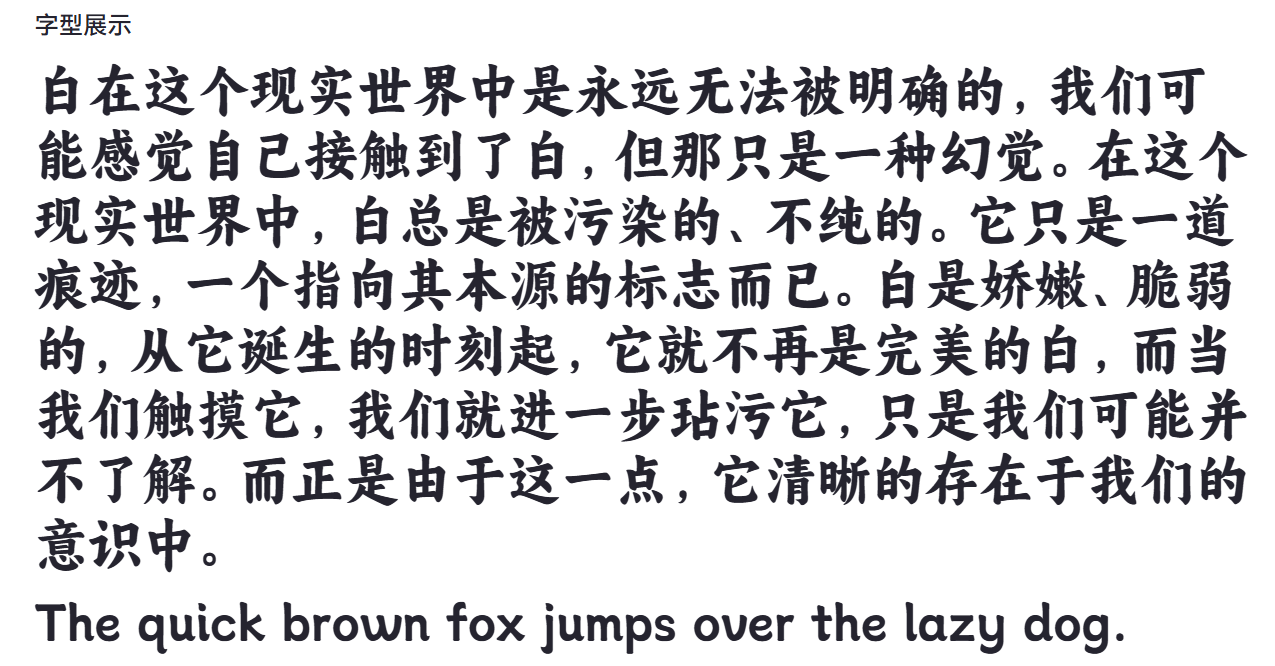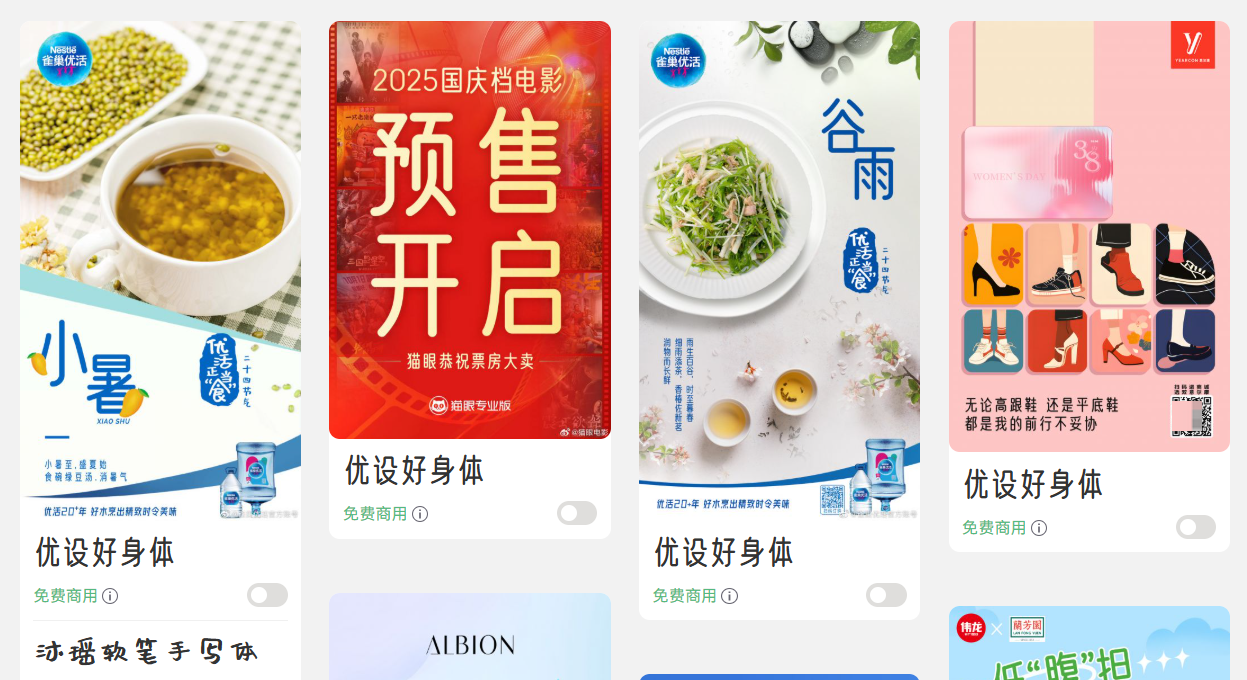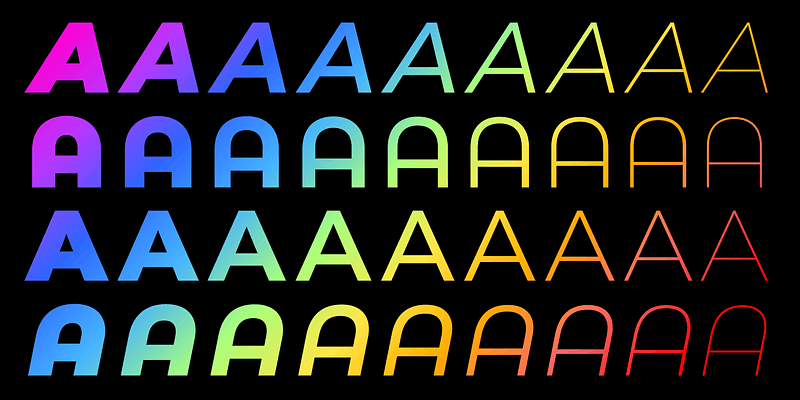
适合电影行业的字体推荐!8款适用于影视设计的字体
从电影海报、片名设计,再到预告片字幕、宣传物料,合适的字体往往能够帮助画面更好地去表达影片主题。在电影中,一款字体不仅承担着信息传递的作用,也会影响观众对影片风格的第一印象。而不同类型的电影对于字体的需求也有所区别,例如悬疑电影通常需要具有沉稳感的字体,科幻电影偏向简洁现代的设计,而文艺电影则更注重字体与画面氛围之间的协调。今天本文整理出了 8 款适合电影行业使用的字体素材,一起来看看有没有适合你的吧!
1、阿里妈妈东方大楷
阿里妈妈东方大楷是一款具有传统书法气息的中文字体,它整体笔画舒展,字体结构中保留了东方书写特点,适合用于具有文化背景或历史氛围的电影设计。如果是古装电影、武侠电影或历史题材电影,阿里妈妈东方大楷也能够帮助画面增加传统文化感。
我们还可以将它与水墨背景、古建筑元素、人物剧照等视觉内容来进行搭配,进一步提升电影中的传统文化氛围。
2、优设好身体
电影海报中的片名往往需要快速吸引观众注意力,因此标题字体需要具备一定辨识度。优设好身体的字形具有极强的视觉表现力,文字排列后能够形成较好的视觉焦点,轻松抓住观众的目光,可以用于动作电影、商业电影、活动宣传海报等设计。
对于要制作电影预告图、宣传海报或者社交媒体推广图片的设计师来说,可以考虑将优设好身体作为标题字体使用。
3、Montserrat
Montserrat 是一款海外常用的无衬线字体,整体风格简洁现代。它最大的特点是结构清楚,阅读体验较好。在电影行业字体的使用场景中,Montserrat 比较适合搭配极简风格、都市题材或者科幻类型电影海报。它不会抢占画面主体,同时能够呈现较强的现代感。在宣传电影时,如果需要同时展示英文片名、导演信息或者制作团队信息,Montserrat 也可以帮助你保持较好的视觉统一。
4、Bebas Neue
在电影海报、影视预告片标题以及商业宣传设计中,Bebas Neue 是比较常用的字体了。因为它的字体比例较为修长,排列后具有明显的视觉方向感,做为标题字体再合适不过。而在一些动作电影、冒险电影或者体育纪录片等类型设计中,Bebas Neue 也能够帮助你来强化画面的力量感。
不过,由于字体风格比较突出,使用时需要注意与背景图片的搭配。如果文字内容较多,则需要合理控制字号和间距,避免影响整体阅读效果。
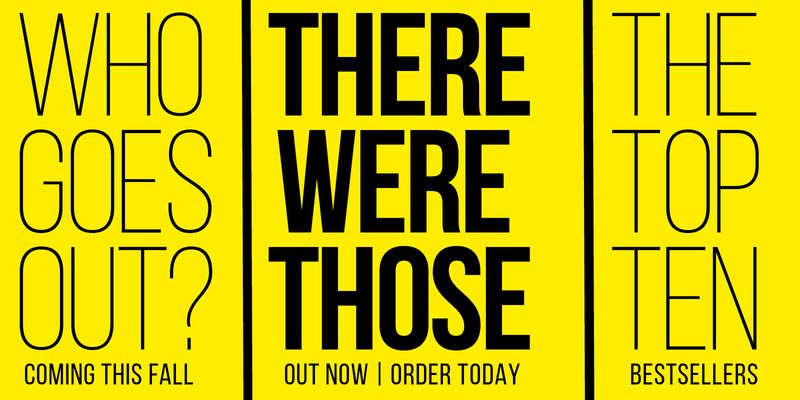
5、Playfair Display
对于艺术电影、历史题材电影或者爱情电影海报来说,字体本身的细节能够增加画面的精致感。而 Playfair Display 这样一款带有衬线特点的字体,可以帮助你保持电影中优雅和稳定的风格。对于一些强调质感和文化氛围的电影设计项目来说,Playfair Display 就比较适合作为片名、章节标题或者宣传语使用。在使用时,我们可以将它与摄影作品、黑白影像、复古色调等视觉元素搭配。
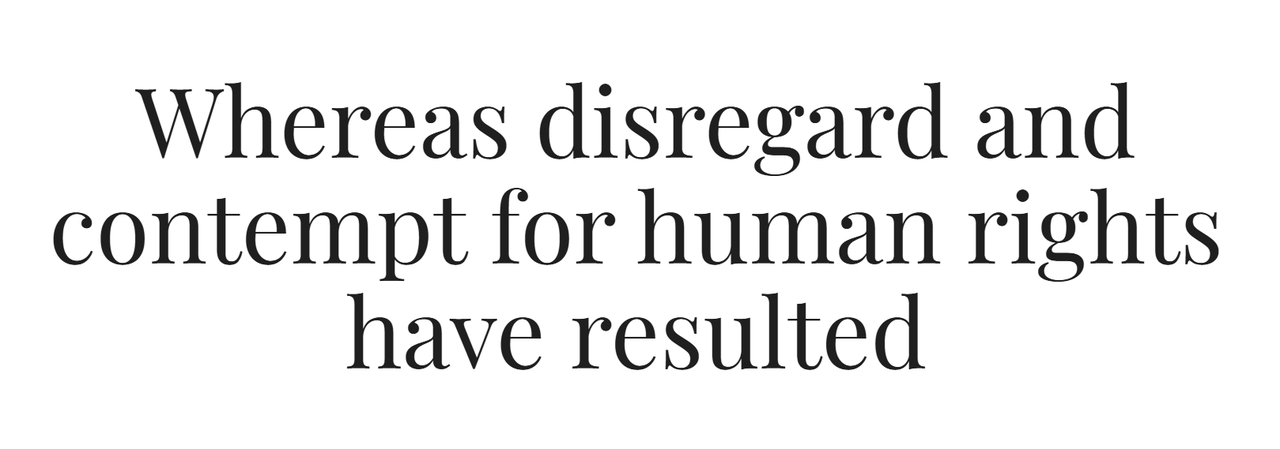
6、Oswald
Oswald 是一款更偏向于功能型的字体,它的特点是文字紧凑,能在有限空间内展示较多的信息,就比如在纪录片海报、影视介绍页面以及字幕设计中,Oswald 可以提高信息传达的效率。还有一些电影节宣传海报、影片介绍页面或者预告片信息页的设计场景中,Oswald 可以兼顾视觉效果设计与可读性。
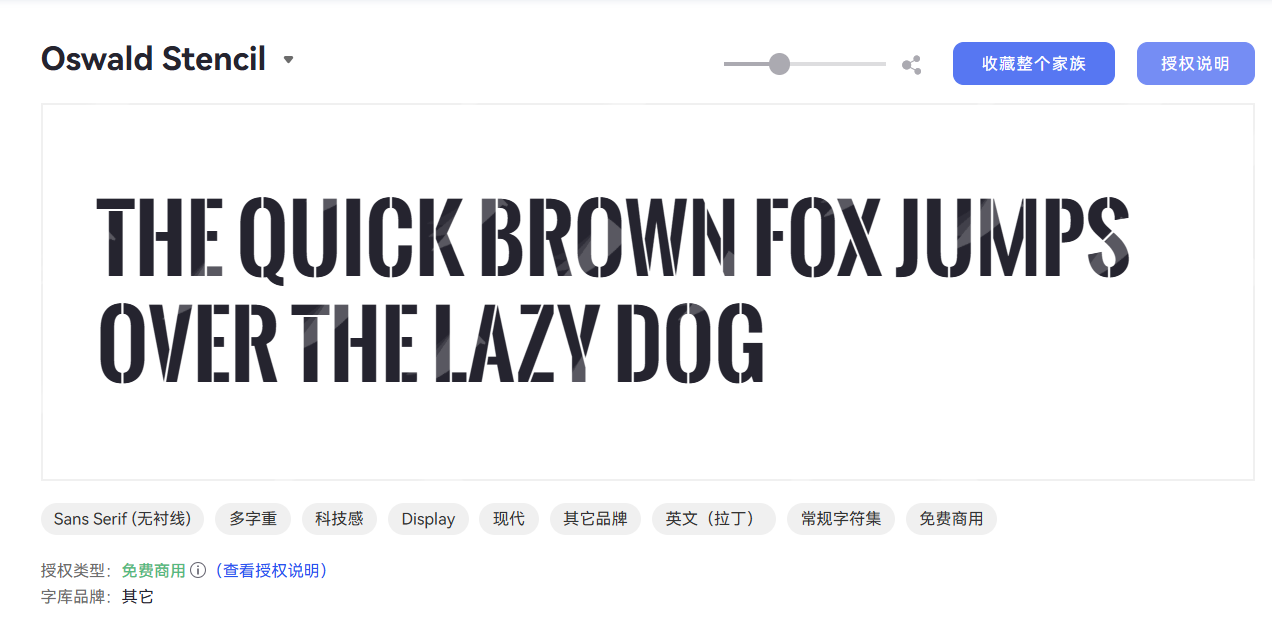
7、Raleway
Raleway 风格轻盈,比较适用于文艺电影、短片作品以及独立影视项目的视觉设计。它字形简洁,同时带有一定设计感,不会让画面显得过于厚重。对于强调情绪表达的电影作品来说,Raleway 可以作为辅助标题或者宣传文字使用。在使用时,可以通过调整字体大小和字母间距来让文字呈现更加舒展的视觉效果。
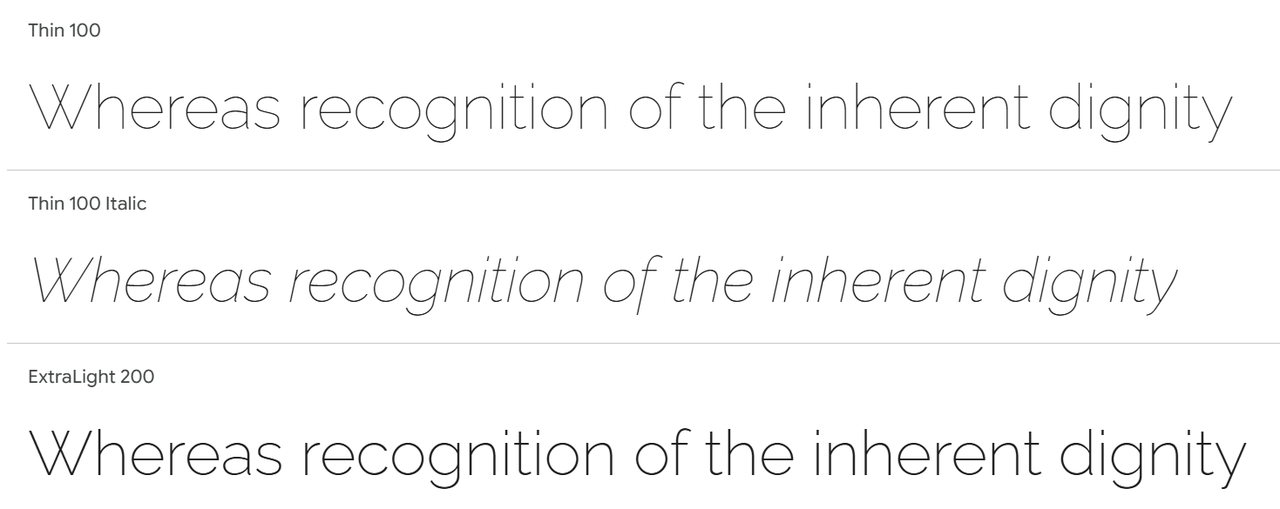
8、Cinzel
在历史电影、奇幻电影以及具有传统叙事风格的影视作品中,使用具有古典气质的字体比较合适。Cinzel 的字体结构带有一定雕刻感,作为电影片名设计,尤其是在搭配古建筑、历史场景或者庄重画面时,可以增强整体视觉的一致性。不过,如果大段文字使用 Cinzel 字体,可能会降低阅读效率。